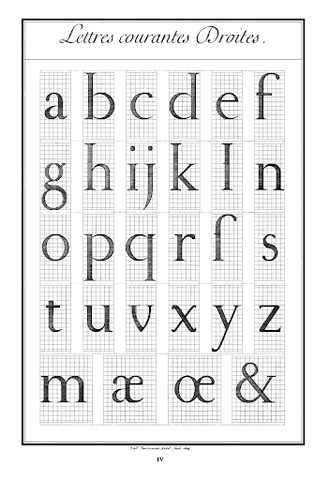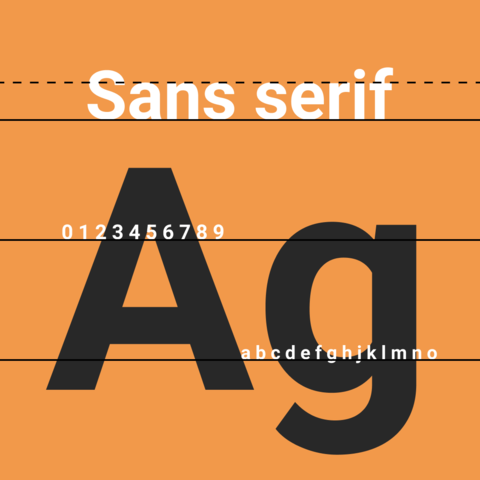
Desarrolló en Alemania una técnica para elaborar moldes de tipo para imprimir letras individuales, con un tipo textura.
Publicó el primer catálogo de tipos que se haya producido (con fuentes romanas, griegas y capitales ornamentadas).
Trabajó con Francesco Griffo de Bologna grabando diferentes tipos romanos, griegos, hebreros y los primeros itálicos para las ediciones aldinas.
Algunos personajes importantes son Henri y Robert Estienne, y especialmente Simon de Colines, que grabó varios tipos romanos, itálicos, versalitas, griegos y latinos. Además de Geoffroy Tory y Claude Garamond, donde el segundo contribuyó con el tipo de letra que lleva su nombre, de gran legibilidad y elegancia.
El rey Luis XIV ordenó la creación de un comité de eruditos para la creación de un nuevo tipo que fuera diseñado bajo principios científicos. Crearon el tipo Jaugeon, con letras de perfecto eje vertical y serifas simétricamente horizontales.
Desde el Medáiles de la Imprimerie Royale hasta el Manuale Tipografico de Bodoni, representan un avance técnico: se hicieron mejoras en las piezas fundidas y en los ajustes de los tipos.
Grabó los punzones, la modificó guiándolos a un nuevo diseño itálico conocido como Romain du roi Louis xiv, labor que continuó hasta 1745, cuando fue reemplazado por Jean Alexandre y Louis- René Luce.
Los tipos artísticos tuvieron en los tipos mecánicos, gruesos y rígidos, una gran competencia.Se empezaron a usar en los periódicos para los titulares de gran puntaje, capaces de llamar más la atención. Joseph Jackson, Thomas Cottrell y Vincent Figgins fueron sus principales exponentes.
Criticadas al comienzo por su simpleza, terminaron imponiéndose gracias a su alta legibilidad. Eran las más sencillas de usar, especialmente para periódicos y medios impresos de lectura masiva, por el avance de la época en la impresión.
Buscar modelos especiales o más de un modelo especial para darle una identidad a las publicaciones se volvió una costumbre. Con los avances en las Monotype, el arte de la tipografía y la impresión, los talleres y los artistas caligráficos, la maduración de las familias tipográficas y la especialización en la materia, la industria de los medios de comunicación impresos se trasladó a una edad de prestigio nunca antes conocida.
Las computadoras incitan a los diseñadores a pedir más y más tipos de letras para cubrir sus inspiraciones creativas y los programas de diseño. Con la llegada de Internet, la tipografía y sus miles de creaciones pasaron a un nuevo escenario, la web, desde donde continúan su fecunda repercusión.